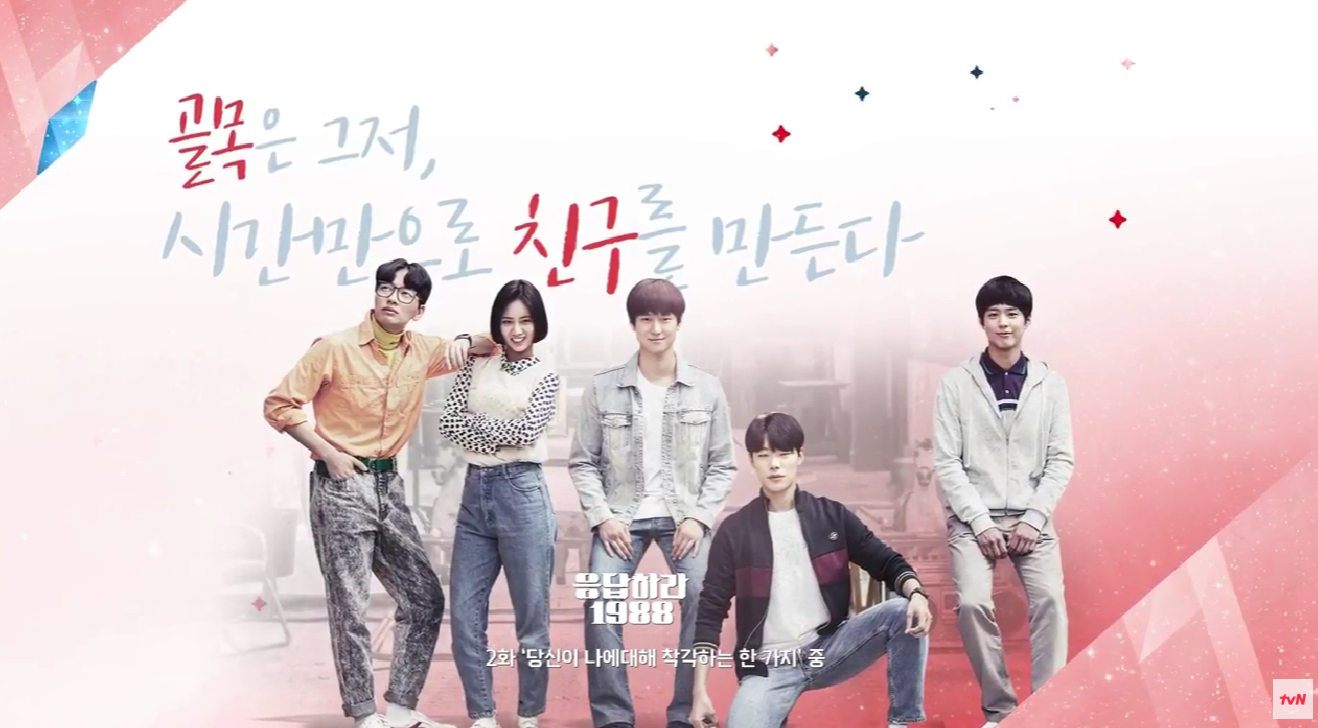
tvN 즐거운 이야기 — CJ E&M에서 배포하는 무료 폰트입니다. 펜으로 힘 있게 써 내려간 듯한 선명한 획과 자연스러운 손글씨의 표정이 살아 있는 서체
tvN이 개국 10주년을 맞아 만들어 무료로 푼 손글씨 서체입니다. 배포하면서 남긴 문구가 그대로 남아 있습니다. tvN이 개국 10주년을 맞이해 tvN의 즐거움을 담은 손글씨를 선물한다는 것입니다.
제작사가 쓴 조형 설명은 손글씨라는 표현 외에 따로 없습니다. 파일에서 재어 보면 획이 부드럽게 흐르고 글자마다 리듬이 살아 있어, 방송 자막에 얹었을 때 딱딱해지지 않는 성질이 있습니다.
굵기는 Light와 Regular, Bold 세 가지입니다. 손글씨 계열치고 굵기가 셋이나 되어 자막과 제목을 나눠 쓸 수 있다는 것이 장점입니다. 영상 자막이나 예능·라이프스타일 콘텐츠에 어울리고 격식 있는 문서에는 맞지 않습니다. 무료로 쓸 수 있는데, 다른 소프트웨어와 묶거나 응용해 재배포할 경우 출처 표기가 필수입니다.